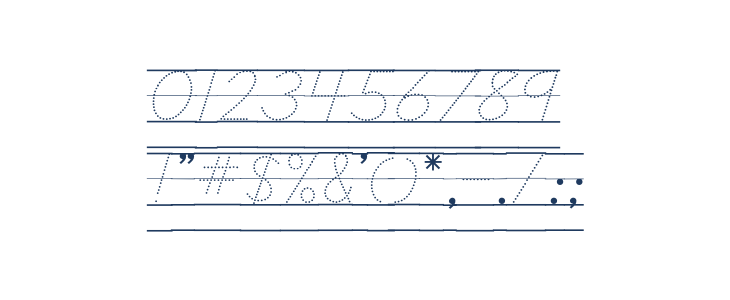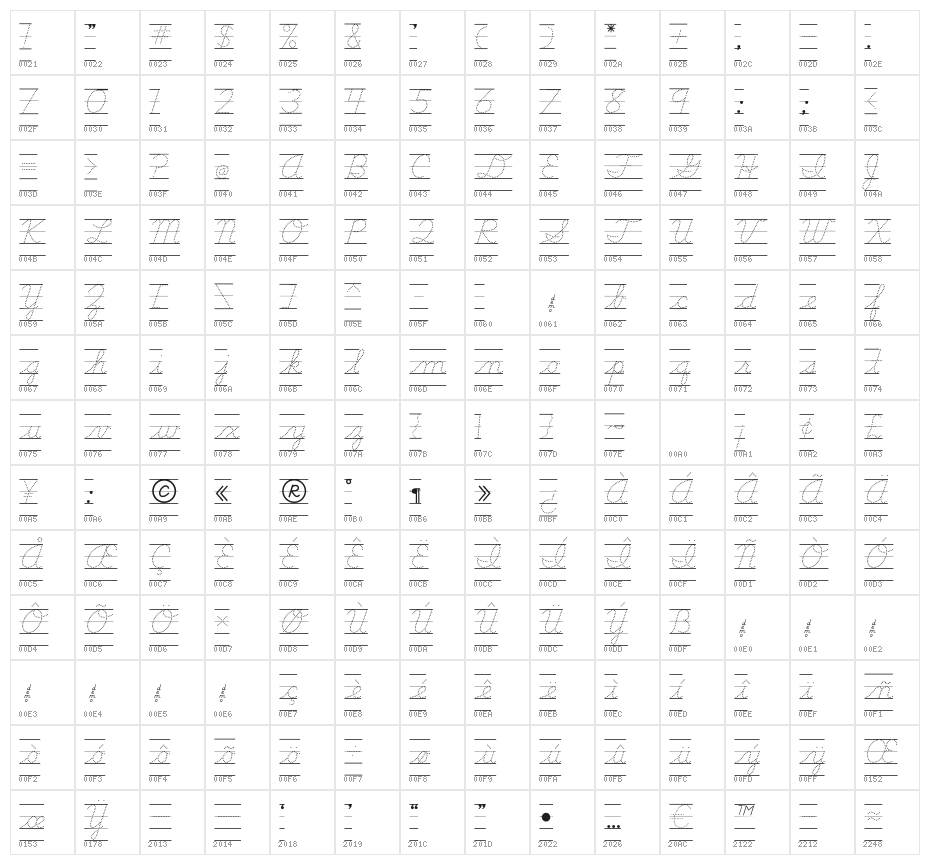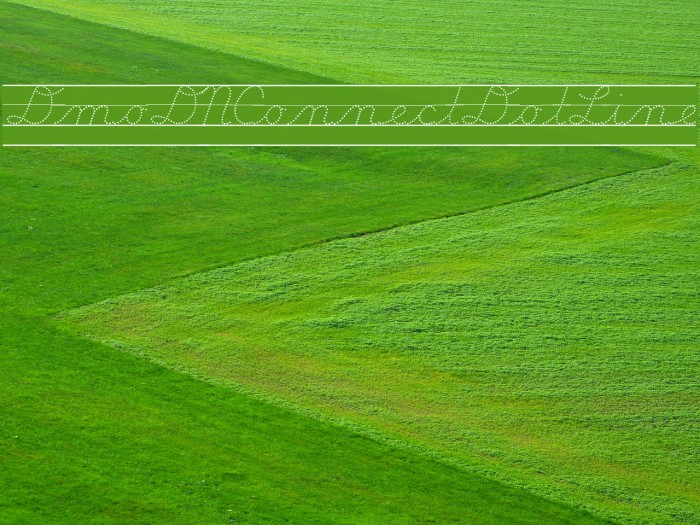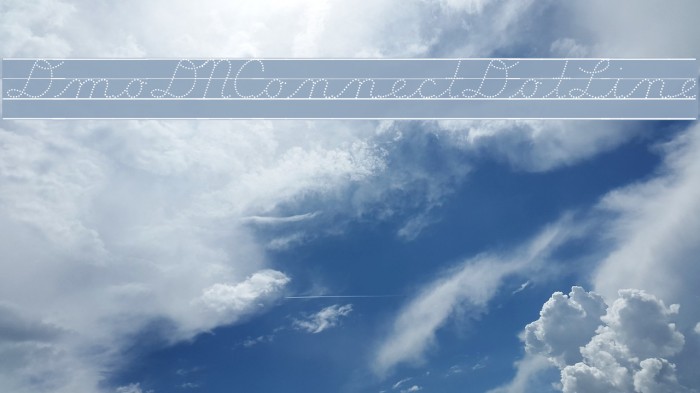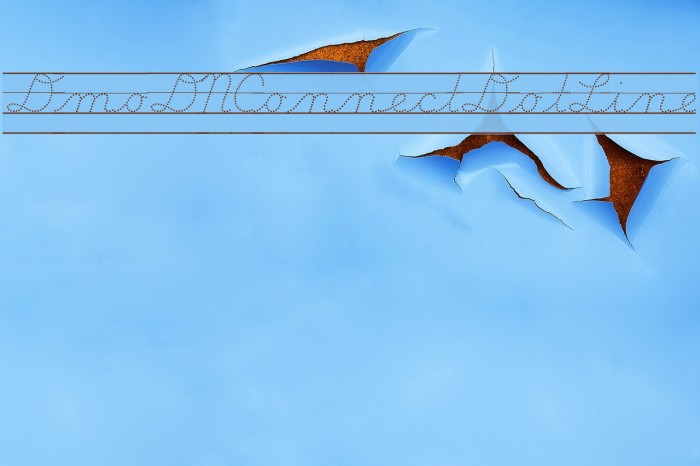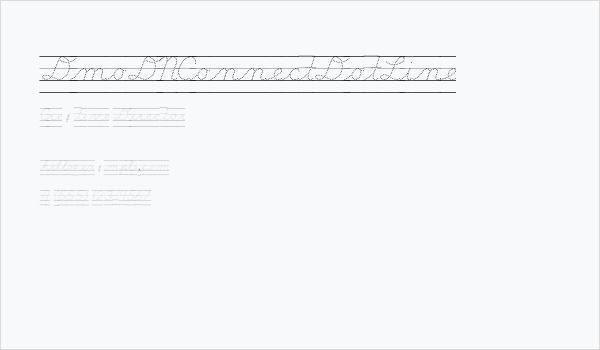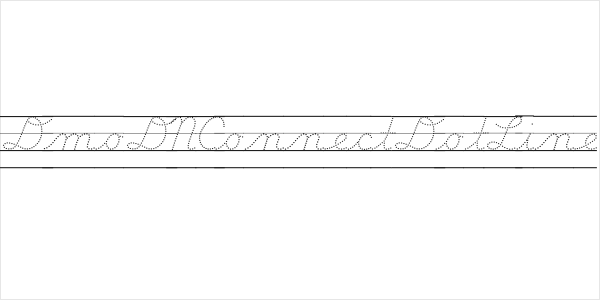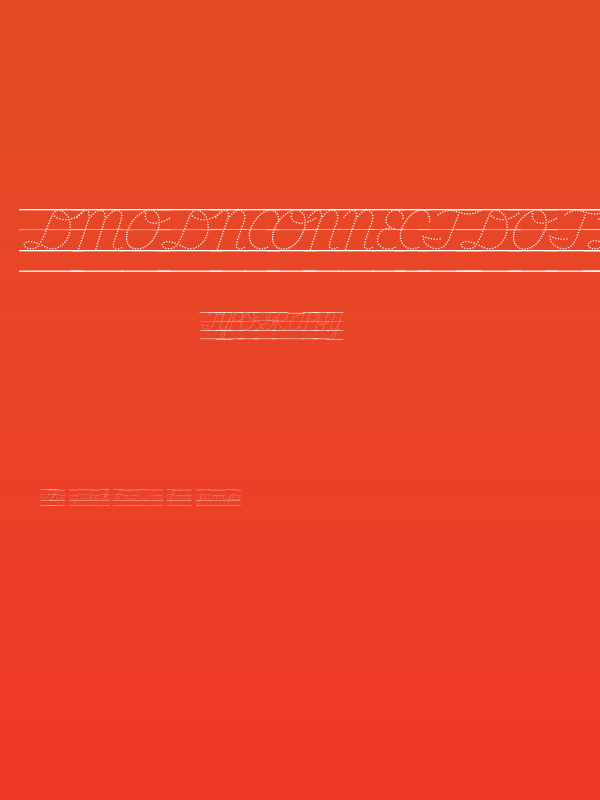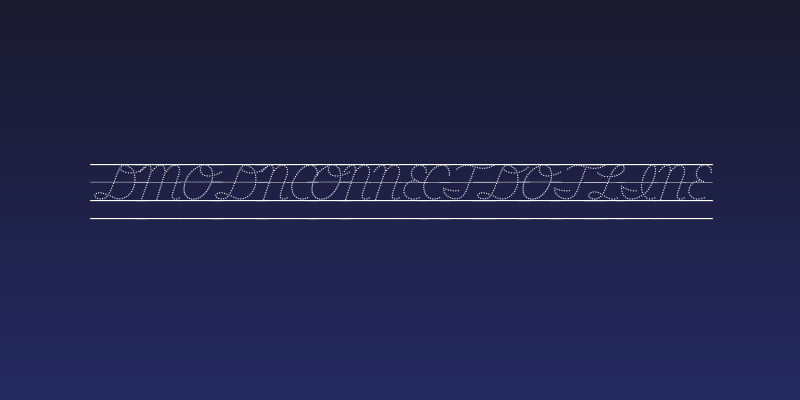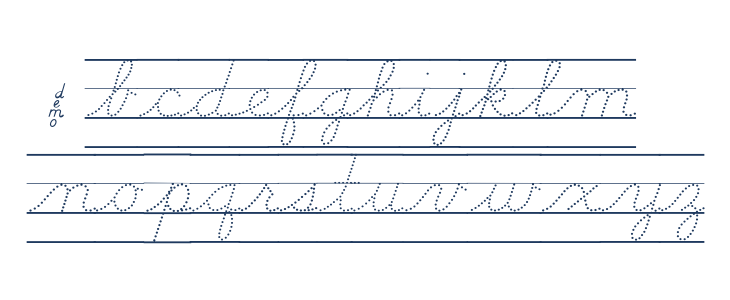
DmoDNConnectDotLine Font
| Общий стиль | Playful, Educational |
| Область применения | Educational materials, Creative projects |
| Рекомендуемые проекты | Perfect for educational materials, children's books, playful branding, and creative design projects. |